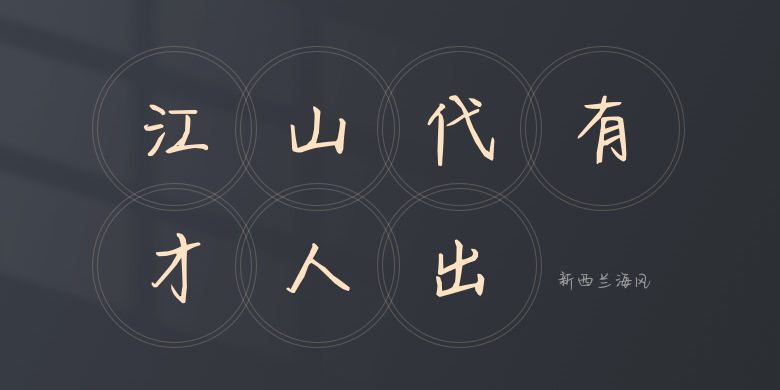
新西兰海风
新西兰海风,这款字体结构工整、笔画清晰,兼顾美观与易读性,适用于标题、正文、海报、包装、LOGO 等多种场景。字形优雅稳定,风格百搭耐看,适配日常排版与创意设计,让文字呈现更舒适、更具质感。新西兰海风一笔一画,皆是细节,以均衡的比例、流畅的线条打造舒适视觉体验,字形端正大气,风格简约现代。无论是商业设计、品牌宣传还是日常排版,都能轻松驾驭,让文字更有格调与力量。新西兰海风字体下载。